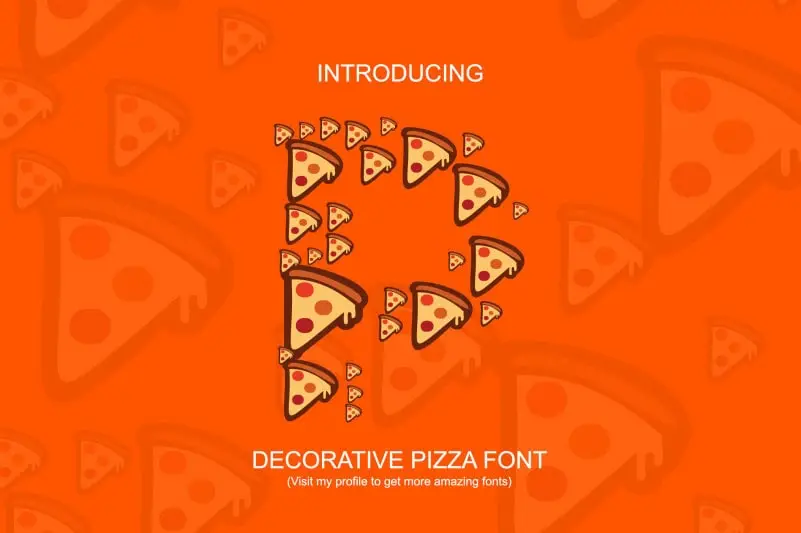
Pizza Lovers Font – Download Grátis
Esta é uma fonte decorativa e deliciosa, onde cada letra se compõe de fatias de pizza. Ideal para quem busca criar algo único e colorido para seus projetos futuros, essa font oferece uma perspectiva divertida e criativa no ambiente do design. Composta por pedaços de pizza, essa font é perfeita para adicionar um toque especial a qualquer projeto gráfico que você estiver desenvolvendo. Delicie-se com cada letra enquanto cria algo inovador e agradável ao olhar. É uma ótima escolha para designers buscando dar um toque único e colorido a seus projetos.